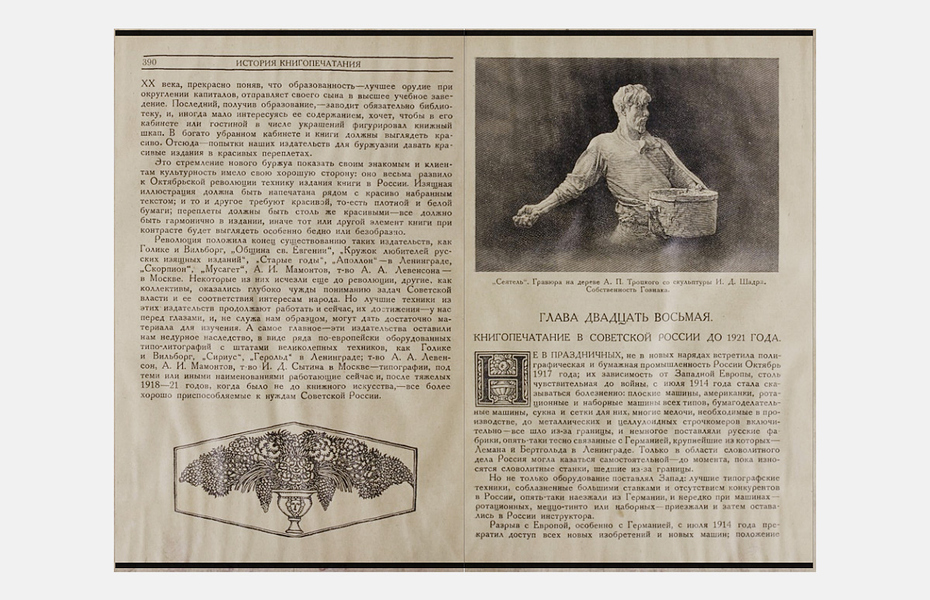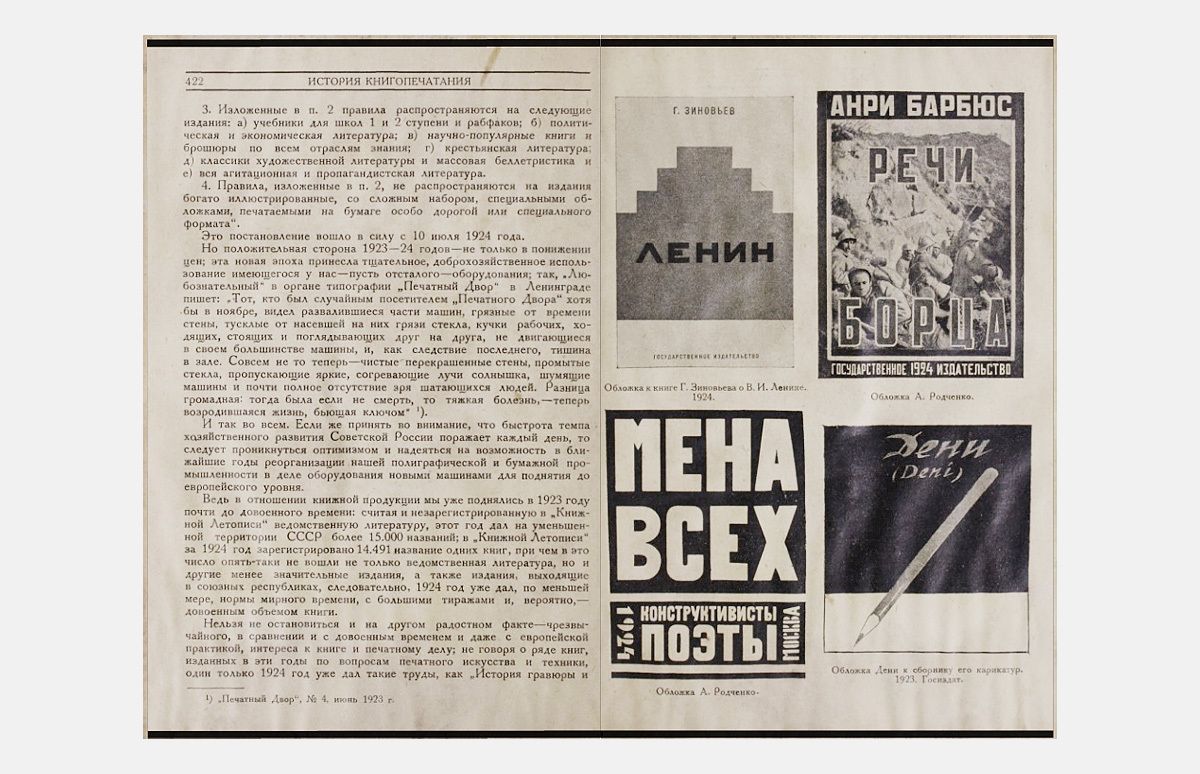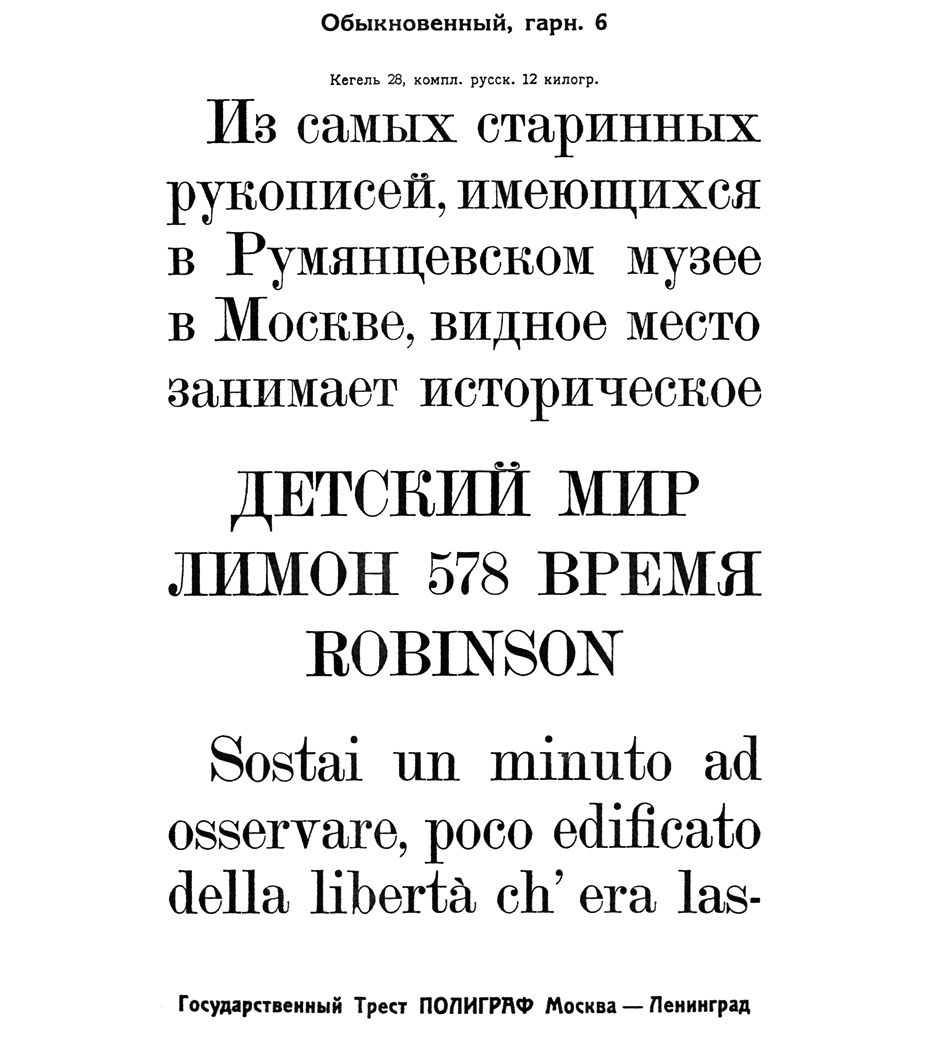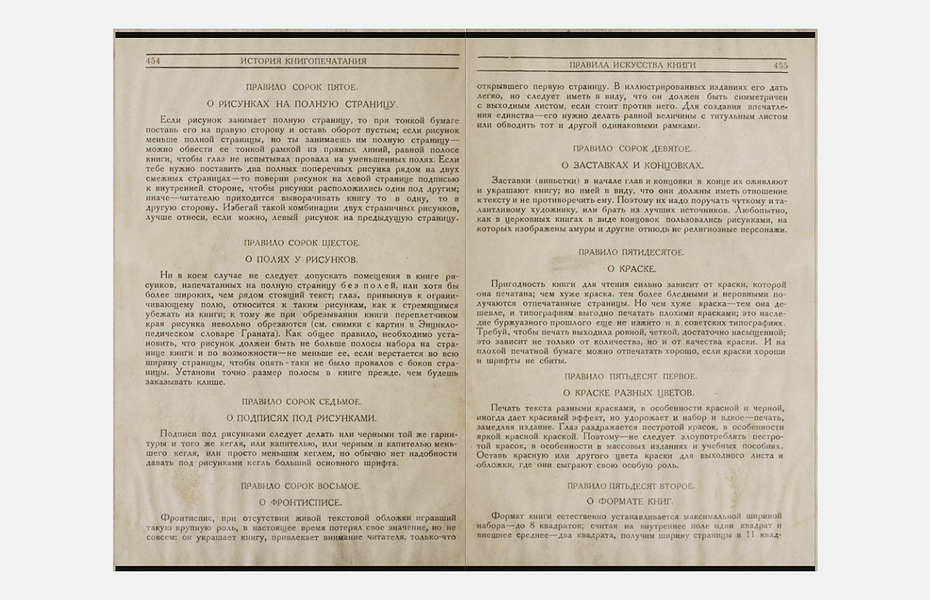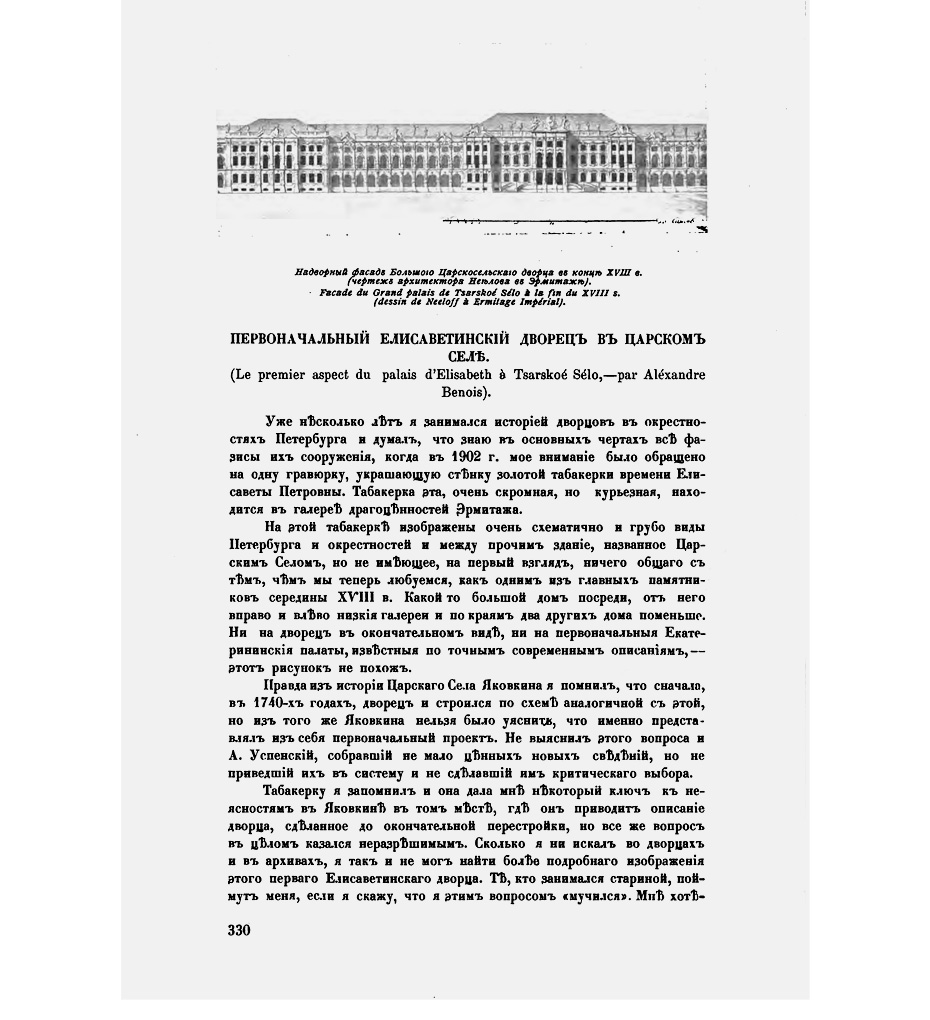
История одного стандарта
В 1930 году в СССР произошло важное событие, существенно повлиявшее на развитие полиграфического оформления изданий на протяжении десятилетий. В феврале Всесоюзным комитетом по стандартизации был принят обязательный Общесоюзный стандарт 1337 «Шрифты гартовые». Вступая в силу с 1932 года, ОСТ 1337 регламентировал ассортимент ручных шрифтов, производимых отечественными словолитнями. Кроме того, фактически он определял и шрифтовой ассортимент типографий, поскольку не вошедшие в него шрифты должны были быть изъяты и сданы для переплавки.
аже сегодня этот небольшой двустраничный документ служит поводом для споров. В статье мы попробуем рассмотреть причины принятия стандарта ОСТ 1337, события, предшествовавшие этому, а также попробуем оценить последствия. Недостаток информации о принятии стандарта порождал и продолжает порождать немало домыслов, догадок и слухов. Так, Леонид Леонов писал в газете «Советская культура» от 3 февраля 1955 года:
Куда пропало разнообразие шрифтов, которыми всегда отличалась русская полиграфическая промышленность? По чьему вкусу остался нам на радость один, лично мне представляющийся если не убогим, то уж никак не пригодным для художественной литературы, «латинский» шрифт, которым набирается, как правило, чуть ли не все, что попадает на типографский двор [...]
Мне сообщили интересную подробность: в своё время в Ленинграде от частновладельческих шрифтолитейных заводов осталось несколько сот различных гарнитур шрифтов и политипажей. В довоенные годы была создана комиссия, которой было поручено пересмотреть это наследие и отобрать всё, что могло бы быть использовано в нашей полиграфии. Комиссия добросовестно поработала и признала годными к употреблению более двухсот гарнитур шрифтов. Но нашёлся некто от полиграфии, который заявил, что нам это имущество не понадобится, хватит и одного шрифта. И вот все пуансоны (стальные формы, с которых отливают буквы) были уничтожены. В познавательном отношении было бы крайне полезно осведомиться, из каких высоких соображений было загублено это неосвоенное культурное наследство, накопленное в течение десятилетий усердной работой русских шрифтовиков.
В связи с переходом на плановое хозяйство с 1925 года, когда был создан Комитет по стандартизации при Совете труда и обороны, в стране началась планомерная работа по стандартизации. Коснулась она и шрифтового хозяйства. Первым шагом в этом направлении было создание трёх каталогов шрифтов треста «Полиграф», последний из которых вышел в 1927 году. Из более чем полутора тысяч шрифтов была отобрана примерно половина. Уже тогда Г. И. Лурье отмечал, что, не создав новых шрифтов, трест «Полиграф» изъял из своих каталогов большую часть имеющихся шрифтов и «результатом этого должно явиться чрезвычайное однообразие внешности наших изданий».
Следующим этапом стандартизации стала разработка общесоюзного стандарта. Принятию ОСТ 1337 предшествовала работа специальной комиссии, состоявшей из трёх подкомиссий. Решение о её создании было принято 24 июля 1927 года на совещании Полиграфического комитета ВСНХ СССР.
Полиграфисты, художники и окулисты должны были, просмотрев и оценив все имеющиеся к тому времени типографские шрифты, определить, какие из них достойны дальнейшего употребления.
Ответственная комиссия
В первую очередь следовало отбирать шрифты, пригодные для применения в массовых изданиях и детской литературе. Хотя итогом работы комиссии был стандарт на гартовые (ручные) шрифты, в процессе её работы рассматривались все шрифты, имеющиеся в наличии, в том числе шрифты для наборных машин и иностранные образцы, не имеющие кириллицы.
Секретарём комиссии был назначен Николай Павлович Проскурнин (1888–1966), который был в то время учёным секретарём Научно-технического совета полиграфической промышленности ВСНХ и ведал вопросом стандартизации. C 1906 года он начал работать наборщиком в своём родном городе Ростове-на-Дону, в 1908 году вступил в профсоюз печатников. Прошёл обучение в Академии графических искусств в Лейпциге, в 1912 году закончил Полиграфический институт в Вене. В послереволюционные годы в Ростове-на-Дону он организовал Краевую полиграфическую школу, где был заведующим, лектором и издателем собственных учебных пособий. Пособия выходили сериями, по несколько выпусков в каждой: «Наборно-типографское дело», «Теория набора» и др. Одновременно он работал техническим руководителем типографии Южно-Донского союза кредитных обществ. Один из его трудов, «Изобретение книгопечатания и начало его в России», из-за нехватки бумаги был отпечатан им на обороте старого табель-календаря на 1919 год.
Николай Павлович руководил совещаниями по реорганизации полиграфического факультета ВХУТЕИНа в Московский полиграфический институт в 1930 году. В середине 1931 года он перешёл на должность старшего научного сотрудника в НИИ полиграфической промышленности, а с 1947 года стал работать в Отделе новых шрифтов. Был награждён орденом «Знак почёта», медалями. Евгений Львович Немировский вспоминал о нём так:
Евгений Немировский
Учёный-книговед,
профессор
В на­ча­ле 50-х го­дов [...] я по­зна­ко­мил­ся с Н. П. Про­скур­ни­ным — ма­лень­ким су­хонь­ким ста­рич­ком, ра­бо­тав­шим в От­де­ле но­вых шриф­тов. Не­смот­ря на на­зва­ние от­де­ла, Ни­ко­лай Пав­ло­вич ин­те­ре­со­вал­ся лишь ста­ры­ми шриф­та­ми. Он со­ста­вил бо­га­тей­шую кар­то­те­ку шриф­тов всех вре­мён и на­ро­дов. Кар­то­те­ка эта, к сло­ву, по сей день не из­да­на и всё ещё пы­лит­ся в ар­хи­вах ин­сти­ту­та. Бу­дет не­воз­вра­ти­мой по­те­рей для на­у­ки, если при оче­ред­ном пе­ре­ез­де её сда­дут в ма­ку­ла­ту­ру.
Скорее всего, к сожалению, именно такая судьба и постигла в итоге эту коллекцию.
Интересно, что многие из членов этой специальной комиссии по подготовке ОСТа ранее или состояли в созданной 20 декабря 1922 году при Государственном издательстве по инициативе К. С. Кузьминского Комиссии по изучению русских иллюстрированных изданий, или принимали активное участие в её работе. Позднее её функции существенно расширились, и она стала именоваться Комиссией по изучению искусства книги. С самого начала деятельности члены комиссии уделяли шрифту большое внимание, считая его одним из самых существенных элементов искусства книги. Как писал в том же году журнал «Печать и революция», «комиссия будет занята, между прочим, выработкой нового типографского шрифта, так как старые шрифты совершенно не удовлетворяют современным требованиям издательского дела, особенно если сравнить их с типографскими достижениями Западной Европы и Америки». На заседаниях этой комиссии, среди членов которой числились проф. В. Я. Адарюков, М. А. Добров, проф. А. А. Сидоров, М. И. Щелкунов, было заслушано множество докладов по теории шрифта.